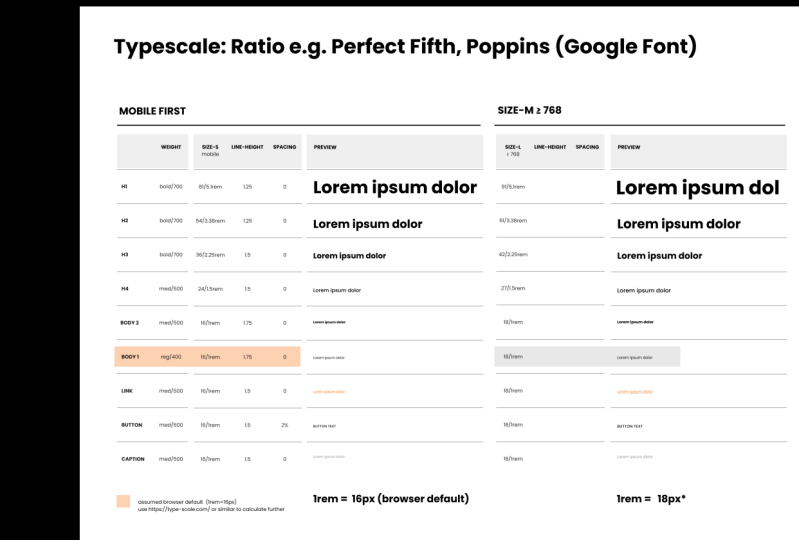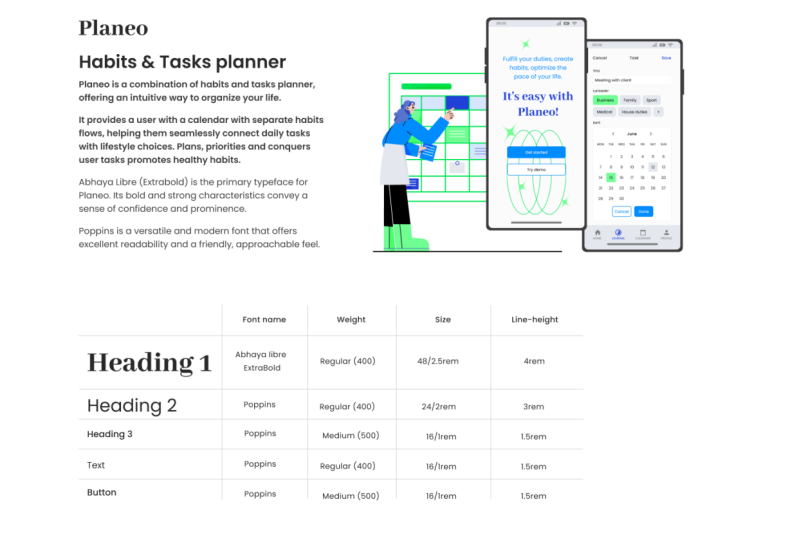
1. 00 fundamentos de tipografia de introdução: Bem-vindo a este curso
abrangente sobre os fundamentos da tipografia de interface tipografia é um
elemento-chave no design, dando vida ao seu trabalho
e orientando Durante este curso de 1 hora, gostaria de dar
uma visão geral sobre um lado mais técnico da
configuração e do trabalho com
tipografia na web Começaremos com o básico,
como onde encontrar fontes, quantas são necessárias
para uma boa configuração de interface de usuário
e por que as superfamílias
são Mostrarei como criar
uma hierarquia sólida
configurando uma escala de tipos de maneiras
diferentes nas quais
você pode fazer isso Aprenderemos como nomear têxteis de forma eficaz
e mostrar
que não interferimos na configuração do código e na otimização de mecanismos de pesquisa E demonstrarei por que é tão importante usar unidades de RM vez de pixels assim que seu
design ganhar vida no código Aprenderemos sobre a
espessura da fonte e as fontes variáveis, e explicarei como a altura da
linha funciona em CSS e o que isso significa
para sua configuração de tipografia Também exploraremos
a importância do contraste de cores e como
verificá-lo e documentá-lo. E o mais importante, veremos
mais de perto como lidar com
a tipografia em
diferentes tamanhos de tela Isso inclui examinar configurações com pontos de interrupção, bem como uma abordagem mais moderna para tipografia
fluida Embora o foco esteja
no aspecto teórico, preenchendo a lacuna entre
design e código, também
daremos uma olhada na implementação
prática
usando ferramentas como Da configuração básica de texto, mais
duas técnicas avançadas como o uso de estilos,
variáveis e modos. Seja você um designer iniciante
ou experiente, isso ajuda você a
refinar habilidades
tipográficas e
2. Visão geral: Provavelmente, não há
nenhum tópico em design cercado por designs melhores
para operar do que a tipografia Não se deixe intimidar. Não se trata de obter um PhD. Trata-se de entender algumas regras básicas
para garantir que sua tipografia
tenha
uma para garantir que sua tipografia E eu vou te mostrar. O importante
é entender que, em vez de ler
cada palavra on-line, as pessoas tendem a digitalizar texto. Então, sobre o que é esse texto? Sim, isso foi o suficiente. E sobre o que é esse texto? É exatamente o mesmo,
mas, como você pode ver, parece muito diferente porque tem uma hierarquia
de trabalho Temos muitos elementos, como tamanho, peso, cor, posição e espaçamento, para criar
essa hierarquia, e vamos examinar
todos eles com mais detalhes Também é muito importante
para mim mostrar um pouco como isso
funciona no código para melhor traduzir e comunicar nossa configuração entre
design e desenvolvimento. Então, durante este curso,
falaremos sobre tipos de letra e fontes e qual é
a diferença real Serif e as
chamadas superfamílias. Vamos discutir
onde encontrar tipos de faces para usar e quantas
precisamos para um bom design de IA. Vamos configurar
uma escala de tipos juntos e vou mostrar maneiras
diferentes de fazer isso. Vou explicar
por que usamos RM para código e pixels ao definir
tamanhos para programação Vou falar sobre nomes e
por que é tão importante
acertar Vamos falar sobre
peso, altura e comprimento da linha,
bem como espaço em branco. E vamos
discutir o contraste, um tópico muito importante quando se
trata de acessibilidade. E, muito importante,
vamos nos aprofundar tipografia
responsiva para garantir que seu texto tenha uma ótima aparência
em todos os Aqui, consideraremos configuração
tradicional
com pontos de interrupção, bem
como uma abordagem mais
moderna usando CSS clamp e discutiremos quando
faz sentido usar Embora este curso se concentre em aspectos
teóricos,
ao longo do caminho, também
daremos uma olhada na implementação
prática
usando ferramentas como Figma, desde a
configuração básica de texto até
técnicas mais avançadas, como o uso de estilos, variáveis e modos, além de
como se alinhar às configurações de design
responsivo E, claro, muitas
dicas e truques, além de alguns
exemplos da vida real ao longo do caminho.
3. 02 typefaceandfont e áudio: Tipo de letra e fonte. O que é um tipo de letra? É um conjunto de caracteres de
design, incluindo letras,
números e pontuação Nesta apresentação, estou usando um tipo de letra chamado Poppins Uma fase de texto inclui
variações como extra negrito, regular,
condensado e assim por diante Uma fonte, por outro lado, é um estilo e
tamanho específicos de uma fase de texto. Portanto, enquanto a fase de digitação se refere ao design
dos caracteres, a
fonte se refere a um estilo
e tamanho
específicos desse design. Por exemplo, Poppins em negrito de
16 pontos, isso é uma fonte. Embora o
termo correto seja tipo de letra, muitas pessoas usam
afeto para significar ambos É uma confusão comum, mas não é grande coisa, desde que você entenda a diferença
em seu trabalho diário
4. 03 Serif, sem serifa e superfamílias: Serif, San Serif
e superfamílias. Existem muitas
categorias de fontes, mas as que você realmente
deve conhecer e San Serif,
pois são fundamentais
para entender papel da
tipografia na legibilidade e na estética do design Identificar a
diferença entre eles é bem simples serapões incluem
um traço extra ou elemento
decorativo
no final da carta, o que pode melhorar a legibilidade no material
impresso ao guiar
o olho por Exemplos clássicos incluem
times New Roman e Garamond. Entender quando e
por que usar cada tipo pode
afetar significativamente a eficácia
do seu projeto. Se você está buscando
um visual tradicional com serapões ou um
toque mais contemporâneo com um Vamos entender isso
um pouco melhor. fontes San SRF,
caracterizadas por sua aparência limpa e
moderna, são uma escolha popular para
telas digitais e conteúdo on-line Exemplos notáveis incluem
Helvetica e Inter. Essas fontes transmitem informações rápidas por
tamanho de forma eficaz, tornando-as ideais
para espaços menores, como rótulos sob ícones ou
interfaces digitais em geral Eles oferecem uma boa legibilidade em vários
tamanhos e resoluções de tela As faces do tipo SP, com seus
elementos decorativos nas pontas das letras, oferecem uma aparência mais tradicional
e sofisticada. Esse estilo clássico é ideal para criar uma atmosfera
de confiança e autoridade, também em conteúdo digital. Eles também podem ajudar
a adicionar um toque de elegância e formalidade
a sites e aplicativos, especialmente em ambientes
como revistas on-line, plataformas
acadêmicas e Embora os serapões sejam frequentemente
associados à impressão, eles também podem ser usados
em design digital Seus seraps detalhados podem ajudar a guiar o olho ao longo
das linhas de texto, tornando-os adequados
para leituras mais longas em telas de
alta resolução,
onde a legibilidade é aprimorada Você também pode incorporar fontes era
e San sera em seu design, alternando entre o corpo do texto do
título, ou talvez escolher um Serafond
para uma No entanto, alcançar
um design harmonioso requer ajustes cuidadosos Os tamanhos de fonte, por exemplo, podem ser exibidos de forma diferente
entre os dois estilos. O que funciona para um pode
não ser adequado para o outro. Se você está pensando em misturar fontes
serafim ou San sera, recomendo usar o que é
conhecido como Como o termo sugere, uma
superfamília é uma coleção de faces
tipográficas projetadas para
se complementarem harmoniosamente,
apesar de uma ser serafim
e a
outra San serp Essas superfamílias geralmente
incluem variações adicionais,
como versões arredondadas, condensadas
ou em forma de tapa Graças ao DNA compartilhado, como a mesma base,
tamanho, proporções e espaçamento, você
pode misturá-los facilmente sem perder a
harmonia geral do seu design
5. 04 Onde encontrar fontes: Onde encontrar fs. Existem três lugares de onde você pode obter seus tipos de letra Se você trabalha para
uma grande empresa, eles podem ter seu
próprio tipo de letra personalizado que
disponibilizarão para você Por exemplo, AB e B têm cereais, uma fonte muito
bonita Agora, é importante
saber que, embora
você tenha o tipo de letra
instalado no seu computador, você só poderá
usá-lo com essa empresa específica A segunda opção é
comprar uma licença. Existem muitas páginas,
como MyFons ou fun shop onde você pode navegar e encontrar fontes incríveis.
Deixe-me te mostrar. Aqui estamos em minhas fontes, e você pode pesquisar fontes, por categoria, por
best-sellers e assim por diante Vou escolher
a categoria e dizer que estamos procurando uma fonte Sansa Então, temos mais filtros aqui à esquerda, o que é muito útil. Podemos ver fontes diferentes aqui
embaixo e temos uma prévia
muito boa. Vamos escolher este. Gosto muito desses
exemplos que eles nos dão para que você tenha uma boa ideia de
como criar com eles. Agora, aqui embaixo, você obtém as informações sobre os
diferentes pesos das fontes e também pode ver
se deseja um pacote familiar ou estilos
individuais Normalmente, faz sentido
optar pelo pacote familiar, e você obtém as especificações
técnicas e, muito importante,
o licenciamento Isso é algo
que você realmente precisa
analisar com seu cliente para
ter certeza de que o que está comprando tem o direito de usá-lo e está ciente do custo. Você pode então simplesmente clicar
em uma vez que você decidir, e então você pode escolher o que você está planejando
usar essa fonte. E então, por exemplo, queremos uma
versão para desktop para projetar e queremos
incorporá-la em um site, e então você pode
ver aqui que isso é calculado por visualizações Você precisaria
instalá-lo em sua máquina para acessar o software de
design de interface do usuário, como o IGMA A terceira opção
será usar uma fonte gratuita. existem alguns pré-instalados no Já existem alguns pré-instalados no
seu computador, como o Aerial Elas são boas como fonte alternativa, mas você pode perceber
que não
são suficientes para o design da sua interface Um ótimo lugar para
digitar rostos gratuitamente são as fontes do Google. É muito popular,
tem ótimas opções e é super fácil de usar. Esteja ciente de que sempre que você
compra algo on-line gratuito
, geralmente vem
acompanhado de alguma troca de dados. Esse também é o caso aqui. É muito pequeno,
absolutamente nada trágico, mas você ainda deve
informar seu cliente se quiser
usar uma fonte do Google A propósito, é o mesmo para o
Google Maps. Vamos dar uma olhada em
como a fonte do Google funciona. mais importante é que
existem muitos, se você clicar nos filtros, poderá preencher
as diferentes fontes. Então, digamos que queremos
apenas o Sanserf ou, se você está procurando suporte a um idioma
específico
, isso é muito útil Agora vamos clicar no
primeiro aqui em cima. Na verdade, estou tomando Open
Sans. Gosto bastante deste. Depois, você pode obter uma prévia. Você também pode digitar o
texto que quiser. Se clicarmos em gFont,
obteremos mais informações. Se você quiser saber mais,
clique em Design, e isso será
relevante para você. Também obtemos todas as informações necessárias para
o desenvolvimento. Eles provavelmente continuam recebendo
o código incorporado
e, em seguida, aqui estão todas as informações
técnicas Eles literalmente só precisam saber qual deles você deseja usar. A propósito, se você
trabalha na Figma
, não precisa
fazer nada Você nem precisa baixar
a fonte, pois tudo
já está pré-instalado no Figma desde que você esteja
usando o Google Fonts
6. 05 Quantos tipos de fontes: Quantos tipos de faces você
deve usar? Então, quantos tipos de faces você
deve ou poderia
ter em seu design. Geralmente, é recomendável não
ter mais do que dois. Você pode ter um tipo de letra
muito dominante, chamado de display,
que faz parte
da marca e usa apenas os títulos principais, como caligrafia ou
algo muito especial, que não é realmente legível e seria Para todos os outros textos, você adicionaria
outro tipo de letra que fosse muito legível
e simples de usar A menos que você esteja realmente
confiante com tipografia ou tenha uma
determinada marca a
seguir, eu
recomendaria ficar
longe dessas fontes de exibição
sofisticadas Você realmente não precisa
deles para um design sólido. No entanto, se você quiser faces de tipos
mistos, como Saraf,
San Saraf, arredondadas e assim por diante, recomendo
que você considere usar uma superfamília, pois elas funcionam
muito bem juntas Então essa seria outra
razão pela qual você pode ter
dois tipos de faces. No entanto, a menos que você esteja
usando uma fonte de exibição ou misturando categorias como
Serif e San Serif, você provavelmente acabará com duas faces de tipo muito semelhantes, e então é muito
melhor usar apenas Pessoalmente, recomendo
começar e
usar apenas um tipo de letra
sempre que possível Para ser sincero, raramente uso mais, e você ainda pode adicionar essa variação
usando tamanhos,
pesos e cores diferentes para
criar sua hierarquia E isso geralmente é
mais do que suficiente. Resumindo, a menos que sua marca exija um tipo de tela
proeminente ou queira misturar estilos
como Serif e San Serif,
onde eu recomendaria
procurar superfamílias, onde eu recomendaria
procurar superfamílias, opte
7. 06 A escala de tipos: Criar uma escala de
texto
significa organizar os tamanhos dos textos de forma consistente, o que é fundamental para
criar hierarquia É como dar a cada texto
seu próprio nível de importância, tornando tudo mais fácil entender e
visualmente atraente Ao configurar uma escala de texto, geralmente
começamos
configurando um tamanho de fonte base, que geralmente se alinha com
o tamanho do corpo do texto, já que é
o mais usado. Uma opção popular são 16 pixels, que também equivale a um RM,
o tamanho padrão que os navegadores É claro que você pode alterar
o tamanho se quiser, mas geralmente é melhor
manter
esse tamanho básico de 16
pixels ou uma RAM. Você pode, é claro, aumentar. Isso facilita a leitura. Pessoalmente, gosto de segui-lo porque ele também se encaixa
muito bem no
meu sistema geral
de múltiplos de quatro e oito,
que eu uso em todo o
meu design para
alinhamento e espaçamento muito bem no
meu sistema geral de múltiplos de quatro e oito, que eu uso em todo meu design para
alinhamento Então, depois de definir
nosso corpo de texto, podemos configurar
nossa escala em torno dele. Não há uma maneira única
de configurar isso. Mas, no mínimo, eu
adicionaria algumas manchetes. Links de botões e
talvez uma legenda. E é claro que você pode ajustar
isso ainda mais às suas necessidades. Por exemplo, você pode ter mais de uma versão
para o corpo do texto. Isso pode variar em tamanho. Ou, no meu exemplo, eu uso estilos enfatizados e
alguns regulares Além disso, talvez seja necessário
adicionar alguma formatação em itálico para citações ou dividir os títulos em categorias de exibição As manchetes exibidas seriam uma grande abertura para chamar a
atenção enquanto
as manchetes normais se misturariam
mais perfeitamente mais Então, isso realmente
depende das necessidades do seu design. Mas mesmo que você possa aumentar sua escala de tipos o
quanto precisar, eu sempre
recomendaria mantê-la mais simples e
condensada possível Em uma folha de estrelas, também
fornecemos informações gerais. Por exemplo, a família de fontes
que vamos usar,
no meu caso, Poppins, queremos dar algumas
informações sobre o tamanho e observar que,
embora em muitos softwares de interface do usuário, ainda
usamos pixels
para definir Em CSS, usamos RAM. Então, eu pessoalmente prefiro fornecer as duas
medidas para maior clareza. Um RM corresponde a 16 pixels, então é muito fácil calcular
isso a partir dos valores de pixels Além disso, queremos
comunicar o peso. Novamente, gosto de dar
o nome que uso no meu software de interface do usuário, bem
como o número CSS. E também adicionamos informações sobre a
altura e o espaçamento da linha Eu estava um pouco preguiçoso aqui
e, no meu exemplo, acabei de
adicionar um pouco de espaçamento
para o meu botão E, finalmente, também
incluímos uma prévia do nosso texto. Normalmente, ao estabelecer
nossa escala de tipos, começamos com o tamanho
menor da tela. Se necessário, podemos
adicionar pontos de interrupção e especificar como nosso arquivo se adapta
em diferentes tamanhos. Existem diferentes
abordagens para isso. Alguns mais modernos nem precisam mais de
pontos de interrupção, mas discutirei isso
em um vídeo separado Portanto, essa visão geral de como
nossa tipografia funciona em nossos produtos em tamanhos
diferentes é realmente
o que estamos procurando Agora, você pode começar seu design
criando uma escala de tipos, mas talvez também queira
começar a projetar livremente
e, quando
se
sentir confortável com o fato de seu design seguir a direção certa, talvez
queira
organizá-la um pouco em uma escala de tipos. E você pode absolutamente fazer isso. Então, o que eu faço é que eu
configurei meu design de forma muito vaga E então, quando sinto que
quero trazer isso de
uma forma mais organizada, escolho a área diferente. Então, eu pego aleatoriamente títulos e
corpos de textos
diferentes e os alinho Também posso ver
quais são semelhantes, então eu os combino em um tamanho e agora posso
criar uma hierarquia Depois de ter a hierarquia e ver de quais estilos preciso, dou a eles alguns nomes,
faço um pedido
e, a partir daqui, posso pegá-la e transformá-la
na escala de tipos de que preciso Você pode abordar da
maneira que funcionar melhor para você.
8. 07 Sistemas de escala diferentes: Diferentes formas de escalar. Você pode escolher um tamanho para sua escala tipográfica de
forma completamente aleatória, se quiser,
honestamente, isso funcionaria Mas em seu design, geralmente
é melhor
ter um pouco de sistema
e consistência. Mostrarei duas abordagens
populares, uma escala fixa usando o sistema de escala de oito pontos e uma escala modular
usando uma proporção Gosto de manter as coisas simples em meu design usando um múltiplo de quatro ou oito para todos os meus
tamanhos, incluindo tipografia Normalmente,
uso múltiplos de oito, como 16, 24 e 32
para meus tamanhos de fonte Eu não sou muito rigoroso com isso, então se eu precisar misturar tudo
para obter a aparência que procuro, eu simplesmente dou um salto maior, mas ainda mantenho a consistência. Isso também torna muito fácil
definir a linha I como um
múltiplo de quatro, o que cria um bom
ritmo vertical no design. Não precisa
ser quatro e oito, mas você notará que esses
números funcionam perfeitamente. Outra abordagem é
escalar com uma proporção. Isso mantém muito bem a
relação proporcional. Você ainda começa com
o tamanho da base e depois multiplica para cima usando a proporção escolhida,
crescendo Você pode jogar com
proporções diferentes para ajustar o crescimento. As proporções populares são feitas
para terceiro, perfeito, quinto e gol e proporção, mas há muito
mais por onde escolher Existem ótimas ferramentas on-line que podem ajudá-lo a configurar isso, então você não precisa
resolver isso manualmente. Deixe-me te mostrar. Há muitas opções
diferentes, e vou usar type
scale com para meu exemplo. No site, deixe
o corpo do texto intocado, mas logo abaixo, no menu suspenso, você pode escolher
proporções diferentes e Você também pode escolher
uma fonte diferente , desde que seja uma fonte do Google, brincar com o peso e assim por diante. No
lado direito, você pode ver uma demonstração de qual
seria a aparência da página. Você também pode
transformar isso em uma visualização móvel. Isso é muito bom
porque você tem uma boa ideia se a hierarquia
é o que você procura Você pode escolher entre
RM e pixels, e você pode simplesmente
selecionar essas informações e traduzi-las para o seu design, bem
como para o seu código Se você estiver optando
pela versão profissional
, também obterá
os trechos de código Não é como se uma abordagem
fosse melhor do que a outra. Você pode até misturar isso e
usar o melhor dos dois mundos. Encontre uma escala de sua
preferência e ajuste
os números para o
múltiplo de oito mais próximo. O mundo é sua ostra. Portanto, a parte importante é que
você tenha uma hierarquia clara. Lembre-se de que existe um sistema para ajudá-lo a não restringi-lo.
9. 08 Por que rem e não px: O que é RAM e por que isso
importa? A RAM é uma unidade CSS que mede tamanho da
fonte em relação ao elemento
raiz da página da web. Normalmente, a tag HTML. O tamanho da fonte raiz é basicamente o
tamanho padrão da fonte de uma página da web. Isso normalmente é
definido para 16 pixels. É como o ponto de partida de todos os outros
tamanhos de fonte na página. Então, todo o resto é
calculado a partir desse tamanho. É claro que podemos alterar
esses tamanhos para nosso design, mas mesmo que não
definamos nada, o navegador já vem
com sua hierarquia embutida É fácil converter
entre RAM e pixels, pois um RM é
igual Portanto, 1,5 RM seria
25 pixels e assim por diante. No entanto, os usuários podem
ajustar o tamanho. No Chrome, por exemplo, os usuários podem acessar
o menu de configurações, escolher a aparência e
personalizar o tamanho da fonte. Isso é crucial para pessoas
com dificuldades de leitura. Não sabemos se eles usam
essa preferência ou o Zoom, mas é essencial respeitar essas preferências
caso estejam definidas. Imagine que você define todos os tamanhos de
fonte em pixels. Para simplificar, digamos que H
um título tenha 48 pixels e o texto do parágrafo, P tenha 16 pixels. Agora, usando pixels
como tamanho de fonte, isso age como um valor fixo e substituirá as configurações do
navegador É como se eles se desconectassem
do tamanho da fonte raiz. Por exemplo, se um usuário ajustou o tamanho da fonte raiz
16-24 em nosso exemplo, a fonte exibida ainda
permanecerá em 16 Isso cria uma barreira de usabilidade porque o conteúdo não se adapta à preferência do usuário Mas se usarmos RM em vez disso
, essa é uma história diferente Vamos pegar a manchete. Na minha configuração padrão, que a maioria das pessoas usará, três RAM são três
vezes 60, então 48, e obtemos o mesmo
resultado dos pixels anteriores. No entanto, o usuário que
alterou um RM para 24 pixels agora tem o título exibido em um tamanho
maior de 72 O melhor é que isso manterá nossa hierarquia intacta pois os diferentes tamanhos ainda se relacionam entre si,
assim como Você também pode encontrar unidades
EM ou unidades. A diferença entre as unidades
RAM e EM é que o RM calcula o tamanho em
relação ao tamanho do fundo raiz,
enquanto as unidades calculam o tamanho em relação ao tamanho do fundo do elemento
pai mais próximo Por exemplo, se o tamanho da fonte
raiz for 16, um RM é igual a 16, não importa onde seja usado As unidades podem se compor
quando estão aninhadas vários elementos com tamanhos
diferentes e herdadas do pai No entanto, o EM, assim como a RAM,
respeita as predefinições do usuário, permitindo designs flexíveis e
responsivos com base na configuração preferida do
usuário Ambas as unidades têm suas próprias
forças e fraquezas, dependendo de como são usadas Desenvolvedores e profissionais qualificados lidam com sua combinação de
forma eficaz, que normalmente não é uma
preocupação para designers. Embora os designers geralmente não
precisem considerar nem mesmo a RAM,
alguns, inclusive eu,
gostam de incluí-la em nossa escala de tipos para reconhecer o
uso de unidades diferentes pelos desenvolvedores. E é muito bom
para evitar mal-entendidos, mas o designer
me deu valores rígidos. Dessa forma, deixamos
bem claro que usamos pixels no design da interface do usuário porque é
assim que ela é configurada, mas ainda queremos respeitar
todas as predefinições do usuário. OK.
10. 09 Peso da fonte e fontes variáveis: Peso da fonte. Entre outros, peso também é um elemento
importante da fonte para
criar hierarquia Já na maioria dos softwares
de design de interface do usuário, você encontrará uma palavra
para o peso. Então, algo como negrito
normal ou médio. Em CSS, isso é
representado por um número. 400, por exemplo, geralmente é normal ou regular e 700 em negrito. Você pode usar esses
pesos ao seu gosto. Mas, mais comumente, os títulos são exibidos em algo
um pouco mais ousado para se destacar e o
texto copiado em algo parecido com o normal, às vezes com
alguns destaques em negrito A única coisa em que você
realmente deve pensar é em não colocar muita luz no texto da cópia para garantir que ele permaneça legível Portanto, é uma boa ideia manter o normal ou o
normal para eles. E, a propósito,
nem todos os tipos de letra são estritamente configurados de 100 a 900 Você também pode obter
algo assim. Realmente
depende do tipo de letra. E outra
coisa importante é que só porque você tem todos
esses pesos diferentes, isso não significa que você tenha que usar todos eles.
Deixe-me mostrar o porquê. Então, aqui estou eu no Google Fonts e agora posso escolher
qualquer fonte que eu quiser. Vamos pegar esse aqui. Se eu clicar nela, posso ver os
diferentes pesos que vêm com essa fonte
específica e posso clicar na fonte G. Agora vamos dar uma olhada no
que isso realmente significa. Vamos dar uma olhada no código
incorporado que obteríamos. Então, aqui você pode ver
isso atualmente. Isso inclui todos os pesos
diferentes. E o que posso fazer agora é
clicar em alterar estilos. Agora posso desligar
todos eles, e você verá que, por padrão, ele
deixará o normal ligado, e agora posso escolher aqueles que estou realmente
usando no meu design. E, claro, eu sempre poderia adicionar mais se precisasse
deles mais tarde. Agora, se você tem um design em que deseja usar
muitos pesos diferentes, e isso é o
núcleo do seu design, então também é bom e
absolutamente possível O que eu recomendo é que dê uma olhada, por exemplo, nas fontes
do Google nos filtros e escolha algo
chamado fonte variável. Portanto, a fonte variável é
um tipo de fonte que permite o ajuste
do peso, largura e outros atributos
por meio de um único arquivo de fonte. Então, assim como em qualquer tipo de fase, isso nem sempre é o
mesmo para todas elas. Por exemplo, vamos clicar aqui no Open Sans e podemos ver
que ele tem três eixos Se dermos uma olhada,
parece que antes, temos nossos pesos diferentes Mas agora vamos clicar na fonte G e ver o
código incorporado que estamos recebendo. Se clicarmos aqui,
então você pode ver, temos o peso,
temos a largura e temos aqui o itálico Então, esses são os três
eixos que podemos mudar. O interessado
é o peso. Então, se clicarmos em um valor, teremos exatamente
como fizemos antes, clicamos em 300 400 ou mais, e isso é
representado aqui. Mas o que também podemos fazer
é ter o eixo completo. Agora você pode ver que isso
é como se tudo estivesse pronto, e não estamos carregando todos
esses estilos diferentes, e isso está apenas dentro
dessa única fonte E observe como diz 300 a
800 ao falar sobre
nossos eixos de peso Isso significa que você não
precisa definir isso para 300 400 e quaisquer valores fornecidos. Você pode
escolher livremente esses eixos e escolher
algo como 415, e você pode
realmente ajustá-los Lembre-se de que
nem todos os navegadores renderizarão isso
exatamente da mesma forma. Os benefícios disso são
um tamanho de arquivo reduzido em comparação com
várias fontes estáticas, criar flexibilidade e design com a capacidade de realmente
ajustar, e você tem um desempenho
aprimorado nas páginas
da Web porque está
diminuindo o tempo de carregamento
11. 10 Altura de linha desmistificante: Entendendo a altura da linha. Ao fazer a transição do design
gráfico para o web design, você encontrará o
conceito crucial de altura da linha Essa é uma chave de propriedade CSS para determinar a
altura total de uma linha de texto. Você pode pensar nisso como uma caixa. Na verdade, é chamada de caixa de linha que envia um texto mais
ou menos verticalmente A altura da linha é
composta pelo próprio tamanho da fonte, bem
como pelo espaço extra adicionado acima e abaixo. Esse espaço é chamado de liderança. E a metade na parte superior
e inferior é chamada, você deve ter adivinhado que
é metade à frente Esse espaço é muito importante
para garantir que o texto seja visualmente atraente
e fácil de ler, além de contribuir para uma
anestesia geral de acessibilidade Vamos dar uma olhada em um exemplo
para entender melhor. O tamanho da fonte do meu
exemplo é de 24 pixels e eu quero uma altura de linha de 1,5. Então isso significa que
calculamos 24 vezes 1,5, e isso é igual Portanto, a altura da caixa
contendo nosso texto é 36. altura da linha pode ser expressa em valores
sem unidade, como
um multiplicador, assim como a usamos
no exemplo, um valor percentual
ou um valor de pixel Enquanto estiver usando seu software visual, talvez
você ainda esteja
usando valores de pixels, adquira o hábito de pensar na altura da linha como um multiplicador e não como um valor fixo porcentagem funciona
muito bem, mas, mais comumente, você provavelmente verá notações
sem unidades em CSS A altura da linha que você selecionará depende
muito da fase
do tipo, do tamanho da
fonte e de sua aplicação. No entanto, você provavelmente
descobrirá que o ponto ideal existe em uma faixa
de 1,25 a 1,75, oferecendo ampla
flexibilidade para seus projetos Se tudo isso é muito novo para você, comece com um
sólido 1.5 para seus designs. Esta é realmente uma
cama segura para você começar. À medida que sua confiança aumenta, você certamente começará
a encontrar alturas de linha, aumentando-as para textos
menores para melhorar a legibilidade e reduzindo-as para títulos para obter Lembre-se de que a altura ideal da linha depende muito do tipo de letra
escolhido,
portanto, trata-se de experimentar
e descobrir o que funciona melhor Em designs com apenas
uma única linha de texto, você pode se sentir tentado a
definir a altura da linha para dois No entanto, exceto em casos raros, eu desaconselharia
essa abordagem. A navegação não é estática,
portanto, uma mudança no painel de exibição pode mover o texto para
uma segunda linha As páginas podem ser traduzidas e repente, o texto
fica muito mais longo, e o conteúdo também
muda com o tempo. Por isso, recomendo
sempre manter
a altura específica da linha que foi definida para o estilo
que você está usando A altura da linha é uma decisão
importante de design,
portanto, certifique-se de
incorporá-la à escala tipográfica e Uma pequena observação: você provavelmente espera que a altura da linha um ou 100% seja a
altura visual exata da fonte. Algo assim e meio
deixando em cima e em baixo. Esse pode ser o caso de alguns, e são os recursos visuais que eu
uso para minhas explicações No entanto, se você mergulhar
nos detalhes mais minuciosos, encontrará pequenas variações Em poucas palavras, um design de fonte
dentro de um quadro específico, conhecido como quadrado n, que serve como uma espécie de
tela para o designer de fontes As métricas da fonte, incluindo aspectos como a
altura de um ascendente, ou
seja, as partes altas, como um m, e o comprimento dos decentros,
algo como um G, podem variar significativamente
dentro do quadrado, dependendo do design da
fonte Com 100% da altura
da linha, o texto pode ou não
tocar nas bordas da caixa. A altura da linha é adicionada
ao quadrado inteiro, não à altura visual percebida, o que pode resultar no que parece ser um espaçamento
visual irregular,
mesmo que a entrelinha
esteja tecnicamente equilibrada Isso geralmente não é
um grande problema, mas pode afetar o alinhamento do texto, especialmente em elementos da interface do usuário, como
botões que aparecem
um pouco fora do centro Um ajuste manual
geralmente é a solução,
e atualizações de CSS, como o corte da
caixa de texto, são planejadas, mas ainda não foram implementadas, mesmo que você já as
encontre em algumas ferramentas de interface do usuário Portanto, é bom
entender esses detalhes, mas não há nada
crucial para enfatizar. Na maioria dos casos, você
notará que apenas trabalhar com a linha especificada
ocultar funciona perfeitamente bem. Ao usar
fontes diferentes juntas, escolher fontes
da mesma superfamília pode ajudar a manter a
consistência nas métricas
12. 11 Uma palavra sobre nomenclatura: Ao observar as escalas de tipos, muitas vezes
você pode se deparar com essa convenção de nomenclatura de
H um, H dois, H três e assim por diante Agora, esses nomes são derivados
de tags de nomenclatura HTML. E eu quero encorajá-lo a evitar esse tipo de nomenclatura em
sua configuração de design de interface e optar por uma abordagem mais
semântica Deixe-me explicar o porquê.
Ao criar um site corretamente, usar cabeçalhos e
outras tags HTML é essencial Essas tags funcionam como a estrutura
que organiza o conteúdo, independentemente de como
elas são estilizadas com Por exemplo,
um H proeminente em uma seção de heróis pode ter tamanho
e estilo completamente diferentes do título principal, que também é H em uma página de
termos e condições. Isso não é importante apenas para a otimização de mecanismos de pesquisa, mas as tags de título corretas também
são cruciais para os usuários que confiam nos leitores de
tela para entender a estrutura
do conteúdo É importante separar o texto
HTML dos
designs visuais, como estilos. Embora trabalhem juntos, cada um serve ao seu propósito
distinto de criar uma experiência de
usuário eficaz. E, a propósito, em web design, usamos texto HTML com
CSS para estilizar, mas nem tudo
funciona dessa maneira No desenvolvimento de aplicativos
para IOS, por exemplo, não
há CSS nem otimização de mecanismos de pesquisa com que se preocupar. Em vez disso, usamos algo
chamado tipo dinâmico, que é apenas o tamanho do texto
com base nas preferências do usuário. Os desenvolvedores podem
começar com as predefinições da documentação e
personalizá-las, se necessário. Ao contrário do texto HTML
com tipo dinâmico, você também pode criar
sua escala de tipos com base nisso, mas sempre certifique-se de discutir primeiro
com o desenvolvimento. Portanto, é muito útil
entender de onde essas diferentes
convenções de nomenclatura vêm
essas diferentes
convenções de nomenclatura e para que
elas foram feitas Se voltarmos ao
nosso projeto de aplicativo web
, uma abordagem semântica
provavelmente será sua melhor aposta Não há uma
maneira certa de fazer isso, mas desde que seja descritiva e permita que os valores sejam alterados, funcionará perfeitamente Uma maneira comum de separar a
hierarquia dos textos,
como usar números de 1 a 6, como usar números de 1 a 6 é adaptar a abordagem do tamanho da
camiseta. Então, estamos usando S, M L e assim por diante, que
também podem ser expandidos. Algumas pessoas preferem uma abordagem mais
descritiva como pequena, normal ou grande Devo admitir que essa
abordagem também traz seus próprios desafios, pois
não há espaço entre esses tamanhos. Portanto, é difícil
ajustar as coisas mais tarde. Você pode se sentir tentado a usar
títulos de dez, 20, 30, como fazemos com cores, o que nos permite
usar entre um tamanho de 25 Mas isso pode ser facilmente confundido
com pixels nesse caso, então eu pessoalmente não
recomendaria usar isso. Para adicionar mais estrutura, você pode criar níveis
usando termos como corpo,
títulos, manchetes e títulos de
exibição Então, isso é muito bom se você
tiver um sistema muito grande. Você também pode ter
várias opções , como
pesos diferentes para uma fonte Novamente, é importante ser
descritivo para que os valores
possam ser facilmente alterados Em vez de chamá-lo de negrito
normal ou 700 ou 500, opte por algo como
enfatizado ou Nomear é difícil e
nomear é importante. Portanto, geralmente recomendo
discutir a nomenclatura o mais
cedo possível com o desenvolvimento para evitar mal-entendidos e usar
as possibilidades de
13. !!! POR FAVOR, ASSISTA !!! Nova interface do usuário Figma em beta: Heads Figma atualizou
sua interface de usuário e você pode ver um novo design
em vez do antigo Atualmente, esta atualização está em versão beta fechada, então nem todos têm acesso ainda. Vou atualizar as
artes e refletir a nova interface assim que ela estiver
disponível para todos. As mudanças são principalmente visuais. Todos os recursos e
ferramentas ainda estão lá, apenas em lugares ligeiramente
diferentes ou com um novo L. Por exemplo, a barra de ferramentas superior foi movida para baixo. O painel lateral esquerdo,
por outro lado, permaneceu praticamente inalterado Agora você pode alterar o
nome do seu arquivo aqui. Você ainda pode ver todas as suas
páginas, camadas e ativos. No
lado direito, você notará algumas mudanças ao
clicar em um design, mas todos os recursos ainda
estão disponíveis. Se você é iniciante e acha a nova interface confusa, pode clicar no ponto de
interrogação
na parte inferior direita e voltar
temporariamente para a interface antiga Isso não influencia
seu design. Dessa forma, você pode
acompanhar os vídeos do curso usando
a interface antiga com muito mais facilidade até que esteja pronto para fazer a
transição para a nova. A FIMA está
lançando gradualmente essa atualização. Se você ainda não tem acesso, também pode
solicitá-lo à FIMA, mas não há garantia, talvez
alguns de vocês precisem
ser um pouco pacientes Talvez o administrador da sua equipe também precise ativar a
atualização para você,
portanto, verifique isso também. A Figma
atualiza o software com frequência,
portanto, espere mudanças e
esteja preparado para se adaptar Os recursos podem se mover como esse
botão de biblioteca aqui
esteve em todos os lugares
possíveis nos últimos anos. Mas não se preocupe, nada nunca se
perderá e você se acostumará a usar o FIMA de uma forma muito
mais flexível Ele tem um
foco muito bom na usabilidade. Portanto, não se trata de aprender
algo de cor, mas de entender o
software como um todo.
14. 12 Tipografia no Figma: Vamos entender como
lidar com texto no Figma. Vamos dar uma olhada rápida
no menu de texto do Figma. Se você selecionar qualquer disposição de
texto na Figma
, no lado direito do painel de propriedades, poderá ver as configurações do texto Aqui podemos escolher um tipo de fase. Podemos escolher o peso.
Podemos alterar o tamanho. E também podemos
escolher a altura da linha. Isso geralmente é definido em pixels. Você pode usar essa
caixa para calcular. Então, se eu quiser 1,5, eu calcularia 16 vezes 1,5. Mas o que eu gosto de fazer é definir isso, na verdade
, em porcentagem. Dessa forma, se eu
mudasse o tamanho
, manteria a
mesma altura da linha. Uma pequena dica, o Figma também
suporta fontes variáveis. Agora, a fonte que estou usando, que é Poppins,
não é uma fonte variável Então, se eu usar essa
lista aqui para o peso
, só recebo as predefinições No entanto, se eu fosse
transformá-la em fontes variáveis, digamos open sans E eu uso o mesmo menu suspenso. Então, por exemplo,
para meus pesos, posso encontrar eixos de
fonte variáveis aqui e agora posso definir o
peso usando os Você também pode alterar o
espaçamento entre letras e
parágrafos Essa seria a distância entre nossos parágrafos se
tivéssemos textos como este Aqui você pode definir como deseja que seu texto
fique na caixa. Eu recomendaria
sempre escolher a altura automática. Isso significa que sua caixa
de texto
respeitará automaticamente sua altura
ou a altura da linha
e, portanto, criará
uma caixa ao redor dela. Você pode alinhar o texto e também escolher qual direção
deseja que o texto cresça Por exemplo, se eu
defini-lo como linha no topo e agora estou adicionando
mais texto, ele
adicionaria um
texto como este. Qualquer outra coisa que
você esteja procurando, basta clicar nos
três pequenos pontos. Aqui você encontra configurações extras,
como decoração de texto,
caixa, corte vertical,
estilos de lista, espaçamento entre parágrafos Já temos isso
no menu principal aqui. Se você quiser ter os pequenos
pontos quando o texto for cortado, você os encontrará aqui Nesse caso, você notará que sua caixa volta
para um tamanho fixo Agora, depois de
configurarmos esse título e o texto ao nosso gosto, queremos salvá-lo
como algo chamado estilo para
reutilizá-lo em Então, vamos dar uma olhada
em como isso funciona. Então, aqui está um
exemplo muito simplificado de uma escala de tipos. Você pode ver, eu quero
configurar uma fonte de exibição, título, corpo, legenda
e um botão E eu quero usar isso
no meu design em geral, bem
como em um componente. Portanto, minha instância aqui deve
herdar esse estilo. Portanto, configurar um estilo é
bem simples. Basta selecionar o texto. E então, no
painel de propriedades do lado direito, você vê o ícone de estilos. Clique nele, clique em mais e agora posso nomeá-lo. Vou chamar
esse display de um. E eu vou fazer o
mesmo com todos os outros. Vou acelerar esse processo
um pouco para você. E, claro, sua escala de tipos pode parecer completamente diferente. Na verdade, este é apenas um exemplo
simplificado. Se eu quiser ter uma
visão geral dos meus estilos, posso clicar na área
cinza da tela
e, no
lado direito, posso ver todos eles. Aqui eu também poderia alterá-los. Então, se eu quiser
mudar alguma coisa sobre o nome ou qualquer um dos
atributos, eu posso fazer isso aqui. Agora queremos aplicar nossos
estilos ao nosso design. Importante: se você estiver
trabalhando com componentes, sempre aplique o estilo ao componente, não à instância. Como você pode ver aqui, aplico o estilo da
legenda à legenda
e, em seguida, seleciono meu título No
menu suspenso, agora
posso escolher o estilo que criei
para o Se clicarmos na instância, você verá que ela
foi herdada automaticamente Para textos soltos como esse, podemos aplicá-lo
diretamente em nosso design. E, por exemplo, digamos
que isso tivesse outro tamanho, então digamos que
fosse muito menor. Então, assim que
aplicarmos nosso estilo, obviamente ele terá
o tamanho
correto e corrigirá toda a altura da linha e tudo o que estiver
salvo no estilo. Se você quiser alterar
ou separar um estilo, basta passar o mouse sobre o estilo e você verá um pequeno símbolo
destacado Se você clicar nele
, ele será separado e você poderá escolher
qualquer outro estilo Você pode usar estilos
assim. Na verdade, isso seria suficiente. Mas desde abril de 2024, também
podemos adicionar
variáveis, se quisermos Então, ainda temos nossos estilos, mas dentro de nossos estilos, esses pequenos blocos de construção, eles podem ser variáveis ou não. Portanto, temos algo
como um tipo de letra, peso,
tamanho, altura da linha,
espaçamento e assim por diante E podemos deixá-los
assim e trabalhar com eles. Está absolutamente bem. Mas assim que você começar a
migrar para um sistema mais escalável, talvez
queira adicionar variáveis
15. 13 variáveis Figma para tipografia: No Figma, também podemos
definir variáveis,
e elas funcionam de forma bastante semelhante às variáveis CSS Vamos primeiro entender
o que é uma variável CSS. Então, aqui temos um
exemplo em CSS, e você pode ver que a cor do link é
definida como uma variável. Em seguida, temos uma classe
chamada link primário, qual adicionamos mais informações,
como o tamanho da fonte, a família do formulário e assim por diante. E você pode ver que
aqui estamos reutilizando nossa variável CSS como
parte dessa classe Também poderíamos configurar todo
o estilo com blocos de
construção ou
variáveis, se quiséssemos. A vantagem é que, se eu
quiser alterar alguma coisa,
digamos, o
tamanho padrão do texto
, eu só precisaria
alterar isso na variável,
e em qualquer lugar em todo o
meu design que eu uso essa variável, isso seria atualizado automaticamente. Vamos dar uma olhada no Figma. Então, na minha configuração aqui, eu tenho uma escala de tipos muito
simplificada, e você pode ver
que tudo isso
já está transformado em estilos. Se clicarmos no fundo da
câmera, você poderá ver uma visão geral
dos estilos, e esses estilos são usados em nossos componentes, bem como qualquer texto solto dentro
do nosso design. Agora, isso funciona
muito bem por si só, então você pode absolutamente
usá-lo assim. Mas assim que você
quiser escalar isso um pouco mais e trabalhar
em um sistema de design, talvez
queira adicionar variáveis. Então eu fui em frente e
criei uma coleção, clique na área de suas câmeras
e, em seguida, vá para as variáveis locais. E aqui eu tenho
várias coleções, e uma delas se
chama brand Typography Posso chamá-lo de qualquer coisa. O Insider já criou
algumas variáveis. Você pode ver que eu criei variáveis
de tamanho de texto. Essa é uma variável de tamanho, e eu tenho 16, 24, 32 e 40, e criei
algumas variáveis para meu peso. Aqui estou usando uma string. Eu tenho uma corda e
depois simplesmente
digito a palavra do
peso que eu quero aqui. Meu caso é normal ou ousado. Também vou
adicionar uma família de fontes. Eu clico no botão de adição e seleciono uma string
novamente para uma família de fontes. Vou
chamá-la de família de fontes e estou usando Poppins, simplesmente
vou digitar Agora, se eu quiser essas pequenas
categorias, lembre-se de que podemos simplesmente agrupar, clicar com o botão
direito do mouse e depois em novo
grupo com seleção, e vou chamar
essa família de fontes. Então, se eu clicar em todas as variáveis, você verá que posso ver
todas as sete variáveis tenho atualmente
na coleção
e, é claro, posso adicionar algumas a elas ou se
preciso excluir alguma. Deixe-me mover a família de
fontes para cá. Você pode organizar
isso ao seu gosto. Se você passar o mouse sobre qualquer variável, poderá clicar em editar variável e agora poderá adicionar
mais informações e também definir o escopo Isso significa que ele
só vai
aparecer nesse campo específico. Agora, estou gravando
isso logo após o lançamento das variáveis
para sites de texto. não temos um escopo
para isso,
mas ele deve ser
lançado e você deve encontrá-lo neste menu Existe um chamado
conteúdo de texto. Isso é outra coisa. Isso significaria que
assumiria o valor real. Substitua seu texto por 16.
Não é isso que queremos. Então, vamos ser pacientes e
aguardar a atualização do escopo. Uma pequena dica, mantenha pressionada a
tecla shift e o comando, e você poderá definir o escopo de várias
variáveis ao mesmo tempo. Ok, ótimo. Então, como vamos colocar essas
variáveis em nosso estilo. O que precisamos fazer é voltar
ao nosso estilo e depois editar. E aqui, você pode
escolher qualquer variável. Por exemplo, se eu
escolher minha fase de texto, agora
posso continuar aqui e ver minha
família de fontes chamada Poppins E agora isso é
transformado em uma variável. E eu posso fazer exatamente o
mesmo com todos os outros. Então, por exemplo, aqui, eu vou aplicar a variável, e agora vou
encontrar minha tipografia, e então vamos dar
uma olhada aqui Queremos ser ousados, então vou escolher esse, e vamos fazer
o mesmo com nosso tamanho. Vamos escolher o
tamanho correto para este. Agora, em altura, atualmente
deixo o código fixo como 150% aqui porque gosto de ter isso em porcentagens ou
algo como 1,5, que é o que
veríamos Mas o Figma atualmente não oferece
suporte a isso em variáveis. Ele suporta apenas valores de pixels , pois estou gravando isso
exatamente quando foi lançado. Então, com certeza, se você estiver assistindo este vídeo um pouco mais tarde, você também pode adicionar a
altura da linha e verificar se percentuais ou unitários a menos valores
percentuais ou unitários a menos, como 1,5,
já estão funcionando. Você pode usar pixels. Pessoalmente,
não sou um grande fã disso. Mas, em geral, você pode
configurar variáveis para todos os campos diferentes
assim que você vê o sinal da variável. Agora, você pode adicionar isso
aos seus estilos existentes. Mas e se você estiver
apenas criando estilos? Isso funcionaria da mesma forma. Vamos pegar um
texto e separá-lo, e agora ainda não é um estilo Então você pode ver que eu já trabalhar com minhas variáveis
em qualquer texto, então eu posso configurar tudo isso e depois salvá-lo como um
estilo mais tarde. Então, você é realmente flexível
em seu fluxo de trabalho. E, claro, se eu
clicar nas variáveis locais e mudar alguma coisa
sobre qualquer uma dessas variáveis
, isso se refletirá
em todo o meu design. Então, neste exemplo,
isso parece muito pequeno porque é um exemplo
muito simplificado. Mas em um sistema maior, isso vai ser uma grande ajuda. Imagine que você está
mudando a família de fontes, você teria que
examinar todos os seus tecidos e designs Assim, você só
precisa alterá-lo aqui, e então isso se refletirá
em todos os seus estilos diferentes. Além disso, se você estiver alterando um tamanho, digamos que você tenha
um tamanho base de 16 e precise aumentá-lo. Então você terá usado esse tamanho de fonte S em
diferentes tecidos, talvez uma versão light,
uma versão mais
ousada e assim por diante Isso será muito
útil assim que você começar a trabalhar em
um sistema maior
16. 14 O espaço em branco é seu superpoder: Espaço em branco, seu superpoder
secreto. Agora, você pode ter
configurado perfeitamente o peso da balança de tipos e a altura da linha, mas ainda
falta alguma coisa. E esse algo
geralmente é espaço em branco. Ao adicionar espaço em branco, você dá ao seu design espaço para respirar e ser
percebido adequadamente. Não há regras fixas
sobre como editar ou onde. Mas veremos alguns
princípios gerais que você pode usar. Então, eu gosto de usar meu sistema de escala de oito
pontos para manter as coisas consistentes Então, tudo é
múltiplo de oito. Por exemplo, entre meu título e meu texto de texto, tenho 16 E então, para distâncias menores, eu uso oito e posso
até descer para quatro. Vou usar isso em
elementos menores, como um botão. E, novamente, esse sistema
existe para me ajudar a
não me restringir. Então, é claro, eu posso
ter um contorno de um pixel ou similar Na verdade, é uma
diretriz geral para criar um ritmo. Você também pode fazer a diferença entre microespaçamento
e microespaçamento Então, entre o espaçamento
dentro de seus componentes, por exemplo, e o
espaçamento ao redor deles Novamente, nesse
espaço em branco maior, como entre as seções, eu uso um múltiplo de oito. Quanto mais você estiver
projetando, mais você terá
a sensação de onde
precisa adicionar algum espaço em branco. Portanto, espaço em branco definitivamente não
é espaço perdido. Está ajudando você
com seu layout. É realmente uma arma secreta. Lembre-se também de
que quanto mais as coisas estão próximas, mais elas são
percebidas como uma só. Então, realmente usa espaço em
branco em seu layout. Isso faz toda a diferença. Uma boa ideia também é sempre dar uma
olhada em como os outros fazem isso. Então, aqui está um exemplo
do sistema de design UBA, e você pode ver que eles
usam incrementos de quatro, e então eles têm alguns blocos de espaçamento
geral
e os usam
em tudo, e os usam
em tudo, desde a configuração de
grades até tamanhos de ícones, e também quaisquer distâncias Em sistemas de design,
você verá que o espaçamento geralmente é
configurado como tokens Aqui está um exemplo
do sistema de design de fios, e você pode ver que eles
têm seu símbolo geral. Tamanho quatro oito e assim por diante, o que corresponde novamente a um
múltiplo de quatro e oito. Então, podemos ver aqui embaixo
que o que eles
fazem é alimentar esses tokens em
uma configuração mais semântica Então, eles entram em
muito mais detalhes. Então, por exemplo,
entre os chips, eles usam esses tamanhos básicos, mas
os definem com muito mais clareza
17. 15 Comprimento de linha ideal: Em comprimento. Em telas maiores, você não quer que o texto flua por toda a largura porque ele simplesmente será muito longo e muito
difícil de ler Diz-se que o comprimento ideal da linha é de 50 a 70 caracteres. Observe que aqui falamos sobre caracteres e não sobre tamanho
físico. Então, isso pode ser bem diferente
para faces de tipos diferentes. Você nunca deve ter
mais de 90 caracteres por linha, porque então
fica realmente impossível de ler. Agora, você não precisa
contar caracteres, mas pode ver que, se seguir essa regra
vagamente, ela já será muito mais agradável e
fácil de ler Além disso,
certifique-se de deixar sua tipografia fluir da maneira que foi projetada e
pretendida Não use a chamada justificação. O que justify faz
é forçar sua tipografia a
caber dentro de uma caixa Agora, às vezes isso pode parecer ótimo se você estiver
projetando com ele. Mas lembre-se de que seu design não
é o resultado final. O navegador não é estático. E quando a tela estiver
se movendo e redimensionando, você terá lacunas bem
feias. Então não faça isso. Vai ser
muito difícil de ler. Sempre deixe a tipografia
fazer o que foi projetada para fazer e
fluir naturalmente
18. 16 Cor e contraste em tipografia: Cor e contraste da tipografia. O contraste é um
aspecto fundamental abordado pelas diretrizes de acessibilidade de conteúdo
da web ou pelas breves WCAG Eles estão fornecendo regras claras sobre os níveis de contraste necessários. E é importante observar que isso não é meramente
uma recomendação. É uma obrigação legal. O WCAG mede o contraste em termos de
diferença de brilho, e isso varia da luz, então um a um, que será branco sobre
branco e 21 a um, que será preto e branco, indicando um alto E isso opera
em um sistema de classificação. Portanto, uma conformidade com A dupla é o
contraste mínimo de que você precisa. Para tipografia, essa proporção
é definida em 4,5 para um para fontes
maiores e
três para um para fontes menores, com o grande
sendo definido de forma bastante vaga, começando com
cerca de 18 pixels ou fundos
menores que estão em negrito,
dependendo da fase do tipo Como isso não está claro, eu sempre tentaria
usar pelo menos
4,5 a um para todos os fundos usados. Idealmente, você escolheria até mesmo
um triplo A. Portanto, você
escolherá sete para um para fundos
padrão e para fontes
maiores, 4,5 para um Então, vamos dar uma olhada em um exemplo. Aqui, eu tenho um fundo
cinza claro e uso uma tipografia vermelha O resultado da taxa de
contraste nesse caso é de dois para um, que fica abaixo do limite recomendado de
4,5 para um Por outro lado, se eu estiver usando essa tipografia cinza escuro
no mesmo plano de fundo, estou obtendo uma
taxa de contraste de 12 para Isso significa que estou até mesmo
cumprindo os padrões triplo-A. Também é importante considerar a espessura e o tamanho
da fonte, pois fontes
menores e mais leves exigem maior contraste em comparação com fontes
maiores e mais ousadas Para ter certeza de que você está obtendo
o contraste correto, recomendo que você sempre
use um verificador de contraste Você pode pesquisar um plug-in de verificação de
contraste em seu software de interface do usuário ou
usar uma
ferramenta on-line como o web aim Portanto, esses verificadores de contraste
funcionam praticamente da mesma forma seja usando um plugue
ou uma ferramenta externa Basicamente, o que
você faz é pegar cor do primeiro plano e a cor
do plano de fundo ou o contrário, e depois
adicioná-las e receber uma proporção Agora, essa é a proporção
que você vai
anotar e comparar com
a proporção necessária. Geralmente, os verificadores de contraste já mostram se
ele é aprovado ou não. Por exemplo, se eu
agora alterar minha cor, posso ver como ela começa a passar. Isso pode ser o texto
ou a cor de fundo. Geralmente, recomendo ter uma visão geral de todas as cores e manter as cores do texto separadas das cores
gerais da marca, mesmo que você possa
usar os mesmos valores. Dessa forma, você pode comparar a cor do texto com
qualquer outra cor e estabelecer regras claras sobre quais cores podem e
não podem ser combinadas. Além do texto padrão, considere
também as cores
do sistema, como alertas
e confirmações E também é uma boa ideia
definir uma cor de
interação clara. Essa seria sua
cor de destaque para botões,
links, ou seja, qualquer coisa
que seja clicável
19. 17 tipografia responsiva com pontos de interrupção: Criação de
tipografia responsiva com pontos de interrupção. Então, o que são pontos de interrupção? São pontos específicos, ou melhor, limiares
ou mudanças ocorrem Dessa forma, os sites podem
ajustar seu layout e estilos para caber em
diferentes tamanhos de tela. Para criar pontos de interrupção em CSS, usamos algo
chamado consulta de mídia A regra de consulta de mídia
é uma forma de aplicar determinados estilos à página da Web somente se
condições específicas forem atendidas Nesse caso, a condição é uma largura mínima de 768 pixels Qualquer coisa dentro dos
colchetes só será aplicada quando a janela de visualização
tiver um tamanho de 768 Vamos dar uma
olhada nisso em CSS. Então você pode ver aqui que eu tenho um título e uma cópia do
texto, bem como duas imagens Em nosso HTML, esse é um
H, o título, o texto
da cópia é P
e, em seguida, aqui temos nossas
imagens com a tag de imagem Agora, no CSS, você pode ver que eu defino o texto para
ter o tamanho de um RM, depois um pouco maior
para o título, e defino as imagens para
ocupar todo o espaço
disponível Então, esses são meus estilos básicos. Agora, ao rolar para baixo, você pode ver que eu
adicionei uma consulta imediata. Quando eu chegar aos 400, vamos
aumentar isso aqui embaixo. Você pode ver o tamanho, então você pode ver quando eu chego a 400, então isso muda no layout. O que acontece aqui é que tudo dentro dos
colchetes fica ativo Eu tenho uma nova cor de fundo, a H é maior e as imagens alteram
a ocupação do espaço. Se eu for ainda maior, você pode ver a segunda consulta de mídia chegando.
Então você pode ver aqui embaixo. Novamente, adicionei uma cor de
fundo, para que ela fique visível, e também alterei a cor H
para ficar ainda maior. Portanto, os pontos de interrupção geralmente são
a técnica mais usada quando
se trata de ajustar a tipografia
a Em teoria, poderíamos
definir pontos de interrupção para cada texto individualmente. No entanto, na maioria dos casos, você provavelmente terá
um conjunto predefinido de
pontos de interrupção para sua escala
tipográfica Isso significa que,
quando a janela de exibição
atinge um determinado tamanho, o layout do texto
se ajusta adequadamente Esses pontos de interrupção podem ser fornecidos por uma estrutura
como o bootstrap, ou você pode
escolhê-los com mais liberdade, principalmente ao adotar uma abordagem
moderna de layout CSS Eles podem já estar em
vigor para outras áreas do seu design, como alterar
o layout geral. Então, na maioria das vezes, faz sentido usar os
mesmos pontos de interrupção Não deixe de consultar a
documentação ou o guia de estilo para obter valores numéricos
específicos se você estiver começando em uma nova equipe E se você for responsável pela
configuração do zero, converse
primeiro com sua equipe de desenvolvimento para saber o que eles
precisam e recomendam. Então, uma vez que conhecemos nossos pontos de interrupção
individuais, a próxima etapa é expandir
nossa escala para cobrir todos os tamanhos Existem diferentes
abordagens para lidar com isso. Vamos explorar a
primeira abordagem, que seria fazer ajustes
individuais. Normalmente, começamos
configurando nossa escala de tipos
a partir do menor tamanho. Quando atingimos um ponto de interrupção, podemos verificar se alguma
alteração é necessária Muitas vezes, um corpo de texto
com tamanho 16 funciona bem em todos os tamanhos, mas os títulos principais
podem precisar de ajustes Obviamente, você também pode ajustar toda a escala
a cada
ponto de interrupção, dependendo de você Nossa segunda opção é expandir
usando nosso sistema modular
, escalando com proporções Podemos manter nossos
valores de RAM consistentes, mas apenas ajustamos o que uma RAM seria igual
em cada ponto de interrupção Por exemplo, em
nossa tela pequena, uma RAM pode ser igual a 16 pixels, depois 18 pixels para nossa tela média e 20 pixels
para nossa tela grande. E então mantemos nosso sistema
geral porque estamos multiplicando o
tamanho da base por uma proporção escolhida Portanto, todos os outros tamanhos
se ajustam automaticamente. Portanto, enquanto 1,5 RAM geralmente são 24 pixels na minha tela média, 1,5 RAM se torna 27, pois agora é 18 vezes 1,5. E para grandes,
calculamos 20 vezes 1,5, então são 30 pixels. É importante
configurar isso sem pixels fixos no código para garantir o suporte
às predefinições do usuário Não se preocupe Há várias
maneiras de fazer isso. Nada muito complicado. Mas vale a pena mencionar
isso, pois no design, estaremos lidando
com um novo conjunto de valores de pixels independentes um
do outro Enquanto estiver em código, isso
permanecerá como unidades relativas. Configurar pontos de interrupção
para tipografia